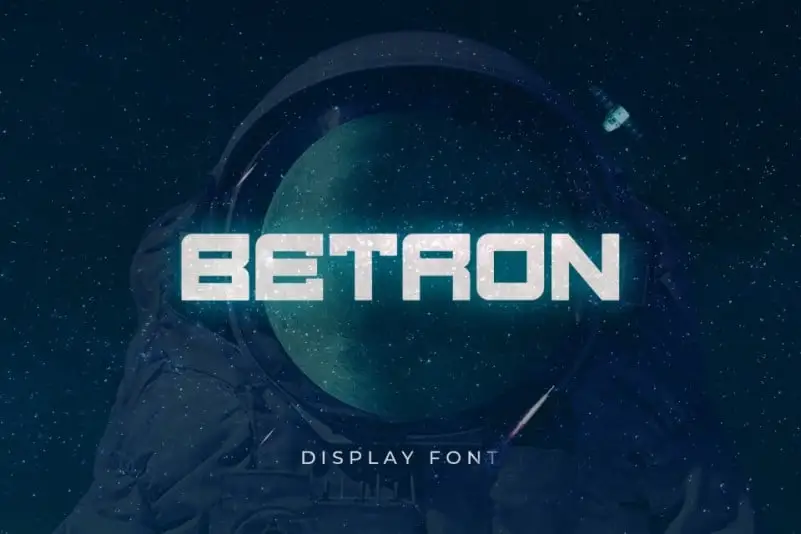
Betron Display Font – Fonte Grátis
Betron Display Font
Betron Display Font é uma fonte versátil ideal para uso tanto em grandes quanto em pequenos tamanhos. Criada pelo designer Din Studio, esta fonte é notável por sua expressividade e autenticidade. Perfeita para projetos de marca, desenhos de móveis de casa, embalagens de produtos e cabeçalhos de revistas, ou simplesmente como uma overlay de texto elegante para qualquer imagem de fundo. Suas linhas marcantes se destacam em qualquer cenário visual, tornando-a um recurso valioso na sua coleção de fontes. Experimente Betron Display Font para adicionar um toque único e moderno a seus projetos gráficos.